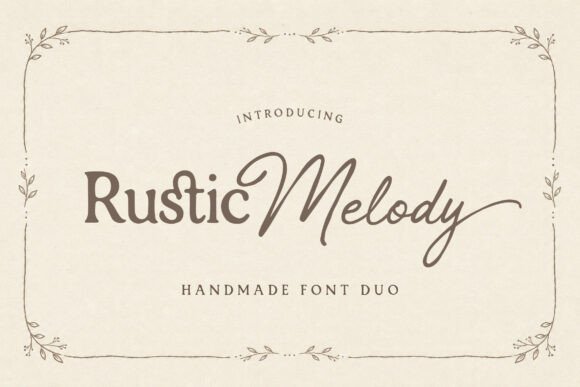
Rustic Melody
Jeśli szukasz wysokiej jakości materiałów, takich jak Rustic Melody, ten pakiet premium to fantastyczny wybór dla Twoich kreatywnych projektów.
Niezależnie od tego, czy tworzysz produkty POD (druk na żądanie), zaproszenia ślubne czy grafiki do mediów społecznościowych, Rustic Melody będzie idealnym wyborem.